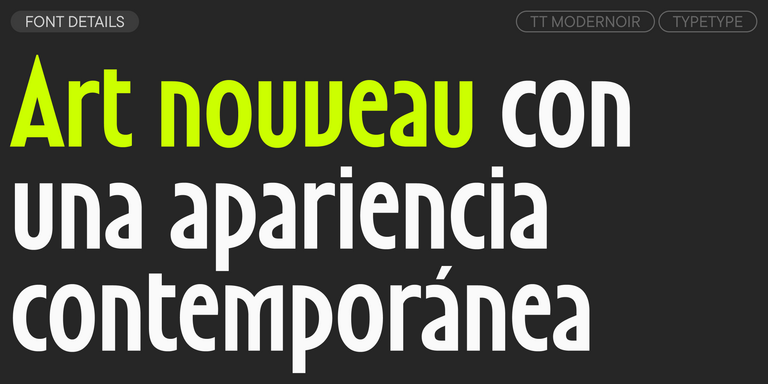
Fuentes similares a Ton
Si estás cansado de las fuentes desgastadas y busca tipos de letra similares a Ton, consulta nuestras principales alternativas a Ton. Estas son fuentes que tienen características similares, pero al mismo tiempo tienen características de diseño nuevas y únicas. Por ejemplo, pertenecen a la misma categoría de fuentes, son adecuadas para los mismos fines y tienen características similares, pero difieren en detalles o proporciones.
En TypeType encontrarás fuentes de vanguardia, tales como Ton e incluso mejores: aquí hay algunas alternativas excelentes y menos comunes a Ton. Utiliza esta lista de fuentes de alta calidad con apariencia Ton que se adapten a tus gustos. De esta manera podrás elegir una fuente aún más adecuada para tu proyecto, ampliar la selección o actualizar tu diseño. Todas las fuentes que aparecen en esta colección están disponibles en diferentes formatos y a precios asequibles, por lo que podrás encontrar una que se adapte a cada necesidad.
Encuentra un excelente reemplazo para Ton e intenta emular un estado de ánimo similar usándolo en sus diseños. Cada fuente presentada en esta página es un doble de la fuente Ton, de hecho, su análogo completo.
TT Runs es una display sans serif muy estilizada y carismática con proporciones irregulares en algunos caracteres.
TT Modernoir es una display sans serif con proporciones dinámicas. Las líneas fluidas y las delicadas formas Art Nouveau se combinan perfectamente con el flujo rítmico y la libertad improvisadora del jazz.
TT Octosquares es una versión renovada, revisada, ampliada y significativamente mejorada de nuestra primera tipografía comercial TT Squares y de su versión estrecha.
TT Bricks es la respuesta para los amantes de la cultura soviética. Hemos intentado retroceder cien años y reinterpretar la era del constructivismo.
TT Prosto Sans es una familia tipográfica para cualquier tipo de tarea. Puedes utilizar esta fuente prácticamente en cualquier lugar.